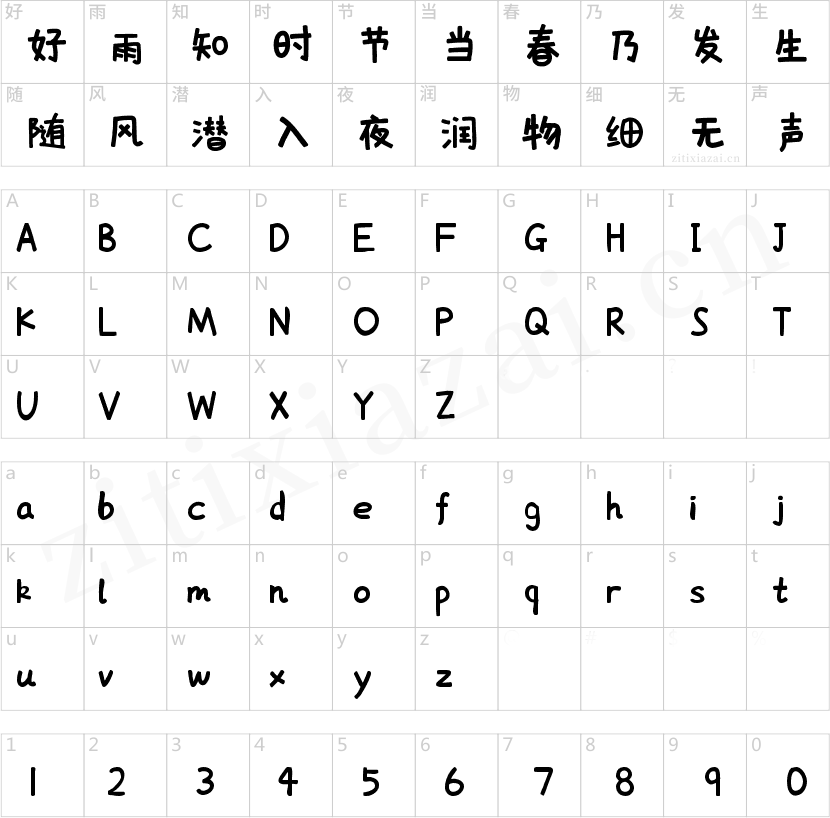
字魂萌趣欢乐体
字魂萌趣欢乐体,这款字体结构工整、笔画清晰,兼顾美观与易读性,适用于标题、正文、海报、包装、LOGO 等多种场景。字形优雅稳定,风格百搭耐看,适配日常排版与创意设计,让文字呈现更舒适、更具质感。字魂萌趣欢乐体一笔一画,皆是细节,以均衡的比例、流畅的线条打造舒适视觉体验,字形端正大气,风格简约现代。无论是商业设计、品牌宣传还是日常排版,都能轻松驾驭,让文字更有格调与力量。字魂萌趣欢乐体字体下载。